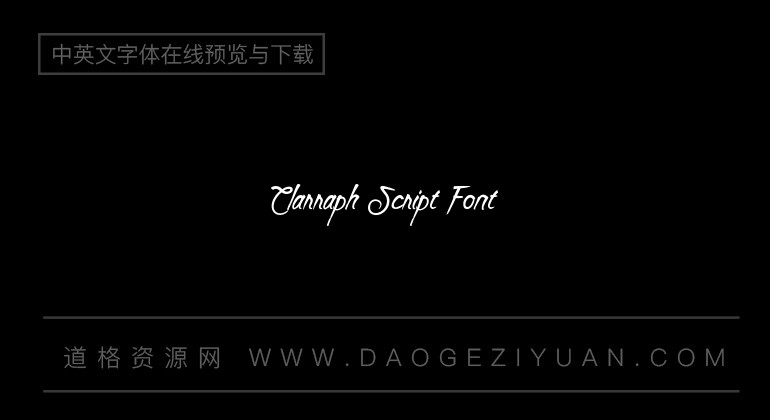
Clarraph Script Font
Clarraph Script是一款优美的手写字体,具有浪漫、自然和优雅的风格。它由一系列连通的字母和符号组成,每个字母都像手写一样,具有轻快的笔画和流畅的曲线。这款字体适用于多种设计场景,如婚礼、时尚、广告、包装等。它的特点是字母之间的连接,使得文字看起来像是手写的,非常适合用于个性化的设计。此外,Clarraph Script支持多种语言,并提供了各种字形,包括粗体、斜体、粗斜体等,方便设计师进行不同的排版和设计。
Clarraph Script Font是一款非常不错的手写艺术字体,具有很好的视觉感,适合于文化类的宣传设计、商业类品牌的广告和产品包装设计以及个性化文字排版等较多场景。